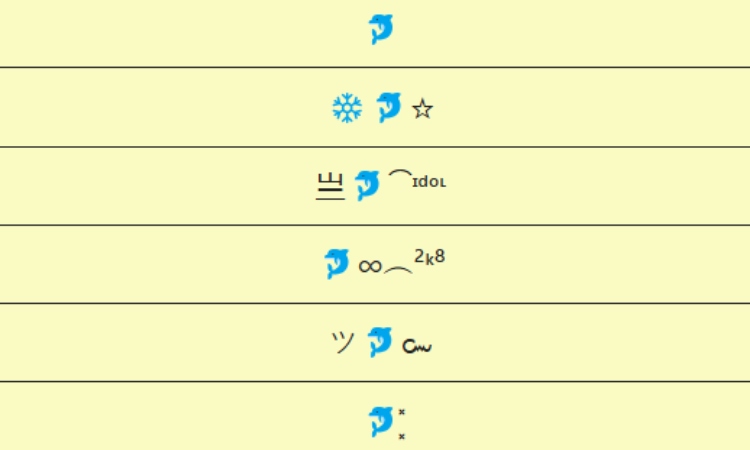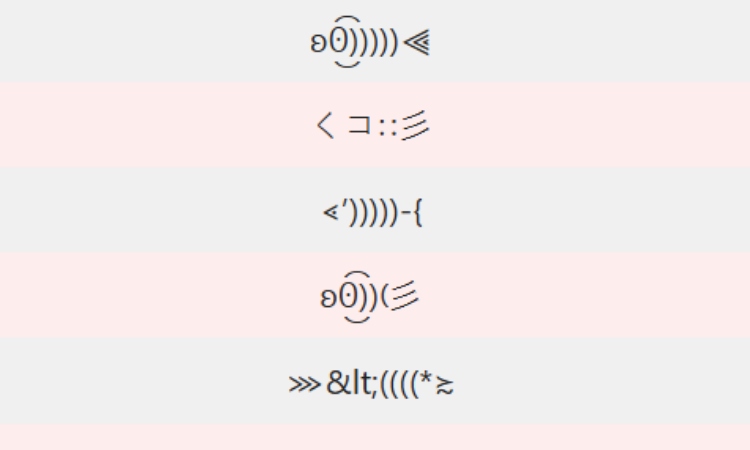
Bộ 88+ kí tự con cá, kí hiệu động vật giúp tên bạn chất hơn
Sử dụng kí tự con cá, ký hiệu động vật trong tên hiển thị, bio TikTok hay tên game đang trở thành xu hướng được giới trẻ yêu thích. Những kí hiệu này không chỉ dễ thương mà còn giúp tên của bạn trông nổi bật và thu hút hơn.
Trong bài viết dưới đây, Mobifonts sẽ gợi ý hàng loạt mẫu kí hiệu con cá mới nhất, icon cá Sấu, cá Heo, kí tự con cá FF, tên ấn tượng, kiểu chữ đẹp, kí tự ngẫu nhiên sáng tạo và các kí tự xáo trộn phổ biến nhất hiện nay. Đồng thời, chúng tôi còn mang đến cho bạn danh sách các ký hiệu động vật khác cực dễ thương.
Kí tự con cá là một dạng kí hiệu trang trí sử dụng biểu tượng Unicode mang hình ảnh chú cá bơi lội đáng yêu. Chúng được dùng phổ biến trong các tên Facebook, bio TikTok, hoặc game như Liên Quân, Free Fire, PUBG Mobile,… giúp tạo sự nổi bật và cá tính riêng.
Không chỉ thể hiện sự vui nhộn hoặc đáng yêu, kí hiệu con cá còn được dùng như một biểu tượng phong thủy, thể hiện sự linh hoạt, khéo léo và may mắn.
Dưới đây là danh sách các kí tự con cá mới nhất, icon cá Sấu, cá Heo, kí tự con cá FF, tên ấn tượng, kiểu chữ đẹp, kí tự ngẫu nhiên sáng tạo và các kí tự xáo trộn phổ biến nhất hiện nay:
Những mẫu kí hiệu con cá thịnh hành chủ yếu nằm trong 2 khối Miscellaneous Symbols and Pictographs (U+1F300–U+1F5FF) và Egyptian Hieroglyphs (U+13000–U+1342F). Tham khảo bảng kí tự con cá mới nhất mà chúng tôi tổng hợp được sau đây:
Biểu tượng |
Tên Unicode |
Mã Unicode |
Mô tả ngắn |
🐟 |
Fish |
U+1F41F |
Cá – biểu tượng chung của loài cá |
🐠 |
Tropical Fish |
U+1F420 |
Cá nhiệt đới – thường thấy trong san hô |
🐡 |
Blowfish |
U+1F421 |
Cá nóc – phồng lên khi bị đe dọa |
🐬 |
Dolphin |
U+1F42C |
Cá heo – thông minh, biểu tượng thân thiện |
🦈 |
Shark |
U+1F988 |
Cá mập – mạnh mẽ, sống ở biển sâu |
🐳 |
Spouting Whale |
U+1F433 |
Cá voi đang phun nước |
🎏 |
Carp Streamer |
U+1F38F |
Cá chép giấy – truyền thống Nhật Bản |
🐋 |
Whale |
U+1F40B |
Cá voi – lớn, hiền, sống ở đại dương |
🐊 |
Crocodile |
U+1F40A |
Cá sấu – biểu tượng sức mạnh vùng nước |
𓆟 |
Egyptian Hieroglyph F034 |
U+1319F |
Cá (ký tự tượng hình Ai Cập) |
𓆝 |
Egyptian Hieroglyph F032 |
U+1319D |
Cá đầu cong (biểu tượng cổ đại) |
𓆞 |
Egyptian Hieroglyph F033 |
U+1319E |
Cá với vây mở rộng (Ai Cập cổ) |
𓆛 |
Egyptian Hieroglyph F030 |
U+1319B |
Cá bơi (cổ Ai Cập) |
𓅾 |
Egyptian Hieroglyph G043 |
U+1317E |
Chim cá (liên quan nước & sinh vật bay nước) |
Icon cá Vàng
Những kí hiệu con cá dưới đây mang phong cách cá vàng – loại cá cảnh phổ biến và dễ thương, thích hợp dùng làm nickname hoặc icon chat cực sinh động. Danh sách các icon cá Vàng kết hợp cùng các kiểu chữ và biểu tượng khác như sau:
🐠
▄︻デ🐠══━一
★彡[🐠]彡★
꧁𓊈𒆜🐠𒆜𓊉꧂
亗🐠×͡×
ϟ🐠﹏
🐠ᴾᴿᴼシ
🐠︵²ᵏ⁸
Icon con cá Mập
Các icon con cá mập là lựa chọn tuyệt vời cho game thủ hoặc người yêu phong cách mạnh mẽ. Dưới đây là một vài gợi ý về icon cá Mập mạnh mẽ và uy nghiêm:
🦈
﹏🦈☆
๛🦈×͡×
╰‿╯🦈┊
☯🦈〄
🦈‿✶
ঔ🦈̾亗
꧁༒☬🦈☬༒꧂
Nếu bạn đang tìm kí tự đặc biệt hình con vật mang cá tính riêng biệt, mạnh mẽ, thì đừng bỏ qua những mẫu con cá sấu. Dưới đây là một số ví dụ về icon cá Sấu cực chất:
🐊
ツ🐊☆
꧁𓊈𒆜🐊𒆜𓊉꧂
×͡×🐊╰‿╯
☂🐊❄
卍🐊×͜×
🐊⃕‿✶
⳻᷼⳺🐊☆
🐊ཽ
ᥫᩣ🐊ㅤूाीू
Icon con cá Nóc
Các mẫu kí hiệu con cá thuộc loài cá nóc thường mang ý nghĩa cảnh giác hoặc độc đáo. Một số mẫu icon cá Nóc thú vị được nhiều người dùng đặt tên như sau:
🐡
꧁༺🐡༻꧂
✿🐡❄
✿🐡ム
🐡シ
🐡҉‿✶
✞ঔৣ🐡ཽঔৣ✞
🐡̬̤̯
🐡⨳
⧼🐡̼⧽
Bạn yêu thích sự thân thiện, vui tươi của cá heo? Ghim ngay những kí tự con cá heo đáng yêu và cực dễ dùng dưới đây trong profile hoặc chat:
🐬
ム🐬☂
❄🐬☆
×͜×🐬×͡×
亗🐬⁀ᶦᵈᵒᶫ
✭🐬☆
🐬∞︵²ᵏ⁸
ツ🐬๛
🐬̐
🐬͓̽
🐬͎͍͐
Bộ kí hiệu con cá FF được dành riêng cho cộng đồng game thủ, tạo tên nhân vật cá tính và phong cách. Tham khảo các gợi ý về kí tự con cá FF mà chúng tôi chia sẻ ngay sau đây:
ʚʘ͜͡)))))⫷
<’))))))↝
くコ∷彡
‧̍̊˙· 𓆝.° 。˚𓆛˚。 °.𓆞 ·˙‧̍̊
⋖’)))))‑{
⋆⭒𓆟⋆。˚𖦹𓆜✩⋆
ʚʘ͜͡))❨彡
<☄))))))彡´¯¸¸.´¯·
⋙<((((*≿
𓇼 ⋆。˚ 𓆝⋆。˚ 𓇼
⋆ ˚。⋆୨୧˚𓆝
ζ°)))彡
<((((゚< >゚)))><
くコ:彡 – shrimp
Những kí tự con cá ấn tượng sau đây sẽ giúp bạn tạo dấu ấn riêng trong TikTok, Facebook hoặc tên game:
ᶜáᵛᶰシᶜᵒⁿ︵²ᵏ⁸
ᏇᎯᎶ丶🅲á亗🅲🅾🅽亗
ᵛᶰシⒸáⒸⓄⓃ™
c̸ác̸o̸n̸
❦ℭᤢO๖ۣۜN︵²ᵏ²
Cá
Cá cute
Vịttt
࿐¢áㅤ¢σи×᷼×
ᵛᶰシČáČƟŊ™
Nếu bạn muốn làm nổi bật tên hoặc mô tả bằng những kiểu chữ nghệ thuật, các kí tự con cá đẹp dưới đây sẽ là lựa chọn lý tưởng: